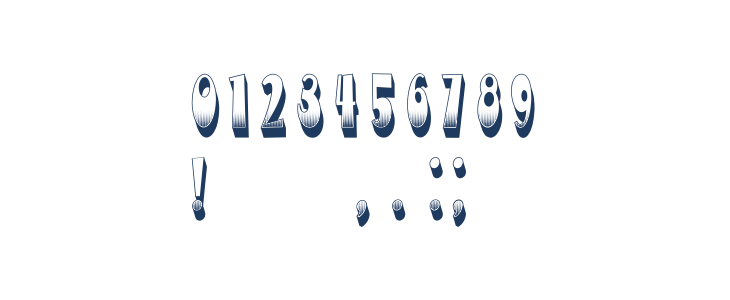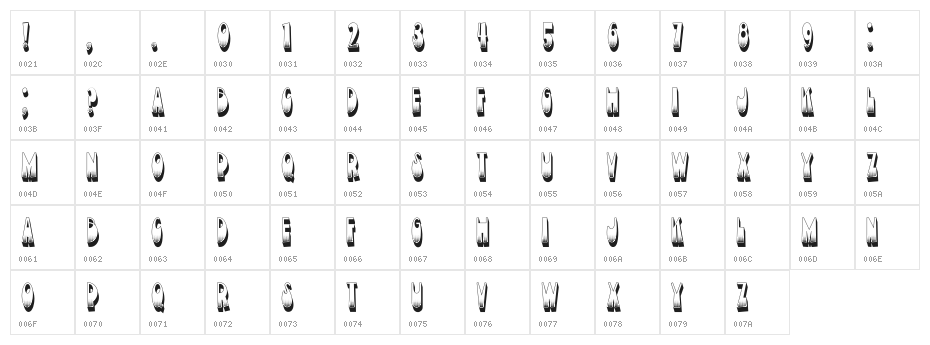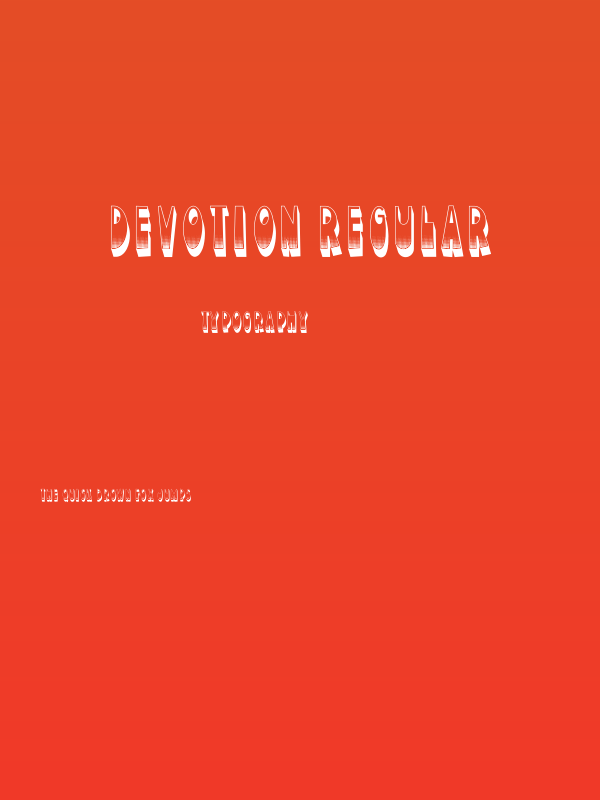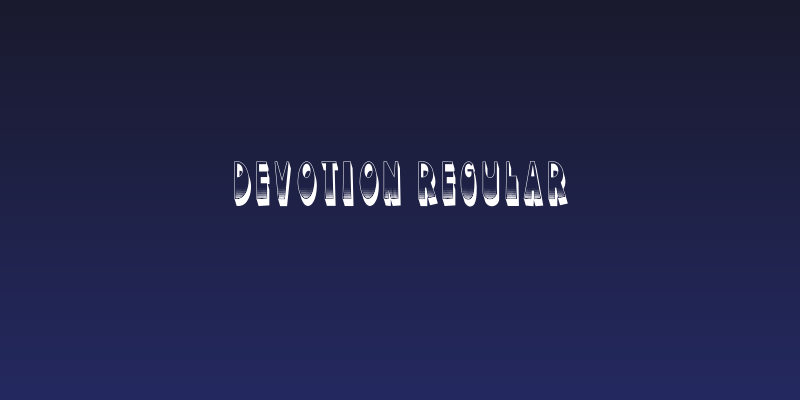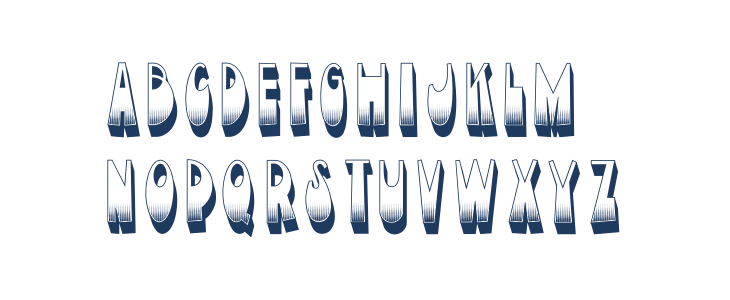
Devotion Regular Font
| Kategorien | Cartoon |
| Gesamtstil | Retro, Decorative |
| Anwendungsfall | Headlines, Posters, Branding |
| Vorgeschlagene Projekte | Ideal for poster designs, retro-themed branding, eye-catching headlines, and creative advertising campaigns. |